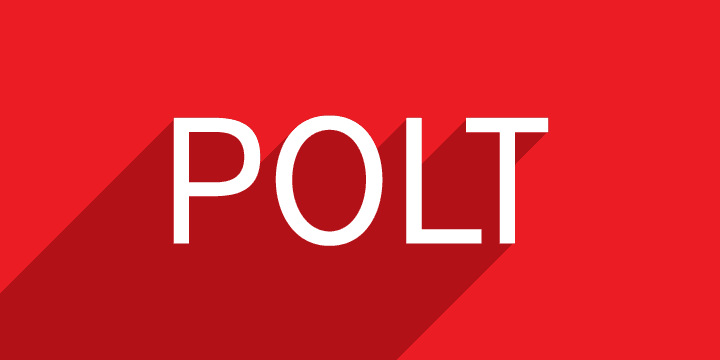
Polt Font Family
A Polt Font Family é uma elegante e moderna fonte gira-faca que se tornará o seu novo parceiro ao trabalhar com textos digitais no Brasil. Inspirada na geometria pura, essa família de caracteres transmite um ar de simplicidade clara e profunda força, perfeitamente adaptada para qualquer tipo de projeto visual. Seja em uma linha séria ou uma tipografia colorida, a Polt mantém um equilíbrio entre modernidade e sofisticação que torna-a uma escolha popular no nosso país. O designer, Hamilton, entrou na arte da fonte com profissionalismo e criatividade. Suas linhas são bem definidas, proporcionando legibilidade ótima mesmo em grande tamanho, enquanto sua tipografia simples mas poderosa dá um toque de distinção ao seu design. A Polt é perfeita para qualquer projeto que exija uma fonte gira-faca moderna e claramente legível, seja ela atraente no layout de jornal ou incrivelmente fácil de ler em sua newsletter digital. Na atmosfera vibrante do Brasil, a Polt se encaixa perfeitamente, oferecendo ao designer um poderoso instrumento para expressar seus ideais através da combinação sutil de formas geométricas e textura. Como resultado, ela não apenas complementa o estilo visual de seu projeto, mas também potencializa-o, tornando a experiência do leitor mais envolvente e informativa.